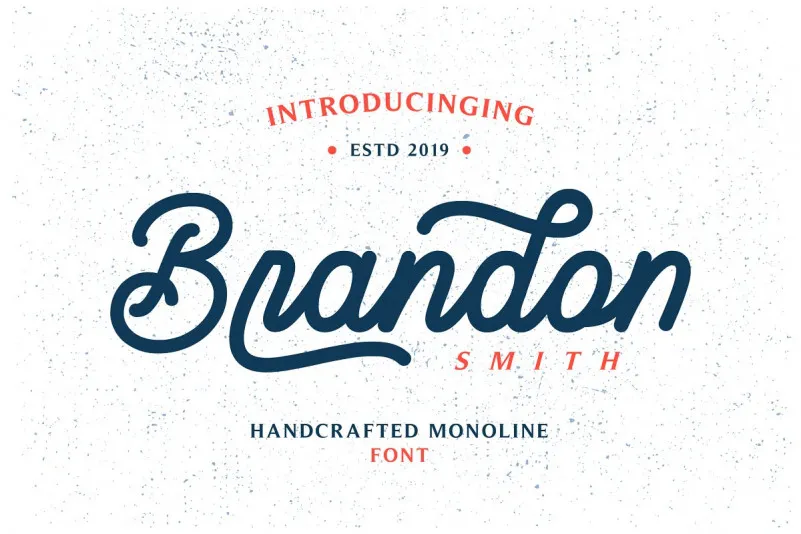
Brandon Smith Monoline Font – Download Grátis
Aproveite essa oportunidade para explorar Brandon Smith, uma fonte script monolínia criada com estilo retro que combina elementos geométricos com swashes e formas alternativas. Este tipo de letra está disponível em dez estilos distintos, sendo particularmente atraente para designers e criativos que buscam um ar vintage combinado com uma sensação moderna. Brandon Smith Monoline é produzido pela Pen Culture, uma equipe dedicada ao design de fontes, e vem em duas versões: Brandon Smith Regular e Brandon Smith Stamp. As suas especificidades incluem alternativas contextuais e estilísticas, formas iniciais e finais, múltiplas opções de gíria para muitos caracteres (acessíveis através da área das guias), suporte multilíngue, ligaturas e números padrão. Este é um verdadeiro tesouro para quem deseja incorporar uma pitada de nostalgia à sua próxima criação visual.